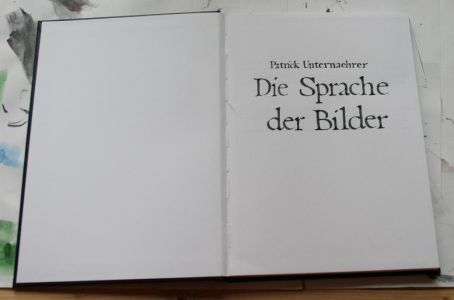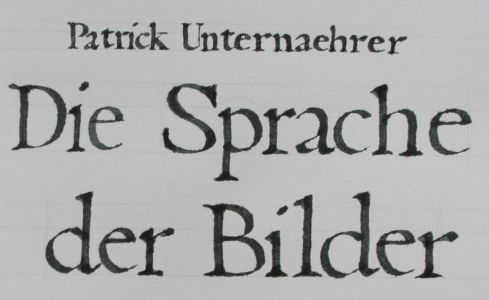
Franz. Renaissance Antiqua mit Breitband Feder schreiben?
Ich habe ein Frage bezgl. der Handhaltung beim Schreiben mit einer Breitbandfeder. Unser Lehrer hat uns immer gesagt (als wir mit dem Pinsel typische geometrische Formen zeichneten) wir sollen mit der Hand nicht den Winkel verändern um gewisse Formen einfacher zeichnen zu können.
Nun versuche ich selbst mit einer Breitbandfeder, von ca. 4-5 Dicke, in dieser Franz. Ren. Antiqua zu schreiben. Aber bei ein paar Abstrichen muss ich einfach sagen 'Wie zum Teufel soll das gehen!?'.
Hier ein Beispiel meiner Probleme (dieser Schriftschnitt ist jedoch für den PC Gebrauch, aber viel ist ja nicht anderst zur Originalen):
Diese Fraktur Schrift ist übrigens auch solch ein Handverränker.
Mein Anliegen ist eigentlich sehr geringfügig mir geht es nur darum wie es der Professionelle Kalligraph macht. Wenn es ok ist seine Hand in andere Winkel zu drehen um solche Abstriche zu erzielen wäre es kein Problem. Mich verwirren halt nur die Worte meines Lehrers (und bei den Eigenschaften steht auch 'schräge achse', also kann man doch nicht einfach die Achse drehen!?)
Die französischen Renaissance-Antiquas waren ja bereits Druckschriften und hatten sich als solche schon ein Stück von der Handschrift entfremdet (ich könnte auch positiv formulieren: emanzipiert). Der Duktus stimmt natürlich noch, aber manches ist so ohne weiteres nicht mehr mit händischen verfahren einfach nachzubilden.
Wäre es Dir möglich, einmal eine solche Arbeit hier zu zeigen?
Nicht zur Kritik zu stellen, nur zu zeigen.
Mich interessiert das.
Mir selbst war das Schriftenzeichnen in meiner Ausbildung immer ein Graus. Ich kann das nicht.
Unser Lehrer hat uns immer gesagt (als wir mit dem Pinsel typische geometrische Formen zeichneten) wir sollen mit der Hand nicht den Winkel verändern um gewisse Formen einfacher zeichnen zu können.
Dein Lehrer hat ja explizit "gewisse Formen" gesagt, was richtig ist. Ansonsten gilt wie überall: Keine Regel ohne Ausnahme. Und als Randbemerkung sei mir die Bemerkung erlaubt, dass das Schriftschreiben wohl die allerbeste Methode ist, das Wesen der Buchstaben zu erfahren und vielleicht sogar zu begreifen.
Dennoch empfind ich es als ein wenig dillettantisch wie ein blöder x Mal den Arm verstellen, aber wie gesagt sind dies ja Druckschriften die bereits ein wenig von der Handschrift 'emanzipiert' ( :lol: ) sind.
@ Georg: Ja, klar! Ich habe ein paar Beispiele hier geuppt
Hier habe ich mich in einer Kapitalis Quadrata versucht:
Diese Schrift habe ich gewählt weil Fibonacci um das 1-2 Jahrhundert lebte. Es wird eine Zeichnung wo ich Studien über Tannzapfen mit Fibonacci-Reihen mache.
Hier haben wir in der Schule eine Anglaise nachgezeichnet (auf einem Raster, deswegen das Transparentpapier - durchgepaust habe ich jedoch nicht wie viele andere in meiner Klasse! 8) )
Hier mussten wir unser Geburtsdatum in einer Schmall Grotesk zeichnen, mit Reisschiene und Technograph Bleistift
Hier habe ich mich in der Fraktur probiert. Noch nicht so schön ich weiss
PS: Wortzwischenräume finde ich bei manueller Kalligraphenarbeit extrem schwierig, beinahe unmöglich zum berechnen, deswegen mache ich das meistens aus dem Bauchgefühl
(Fibonaccis Geburtsdatum wird allerdings auf ca. 1170 datiert. Man hat keine Aufzeichnungen über das tatsächliche Geburtsdatum gefunden.)
Die In der Kalligrafie gibt es keine Möglichkeit, Wortzwischenräume zu berechnen. Das Bauchgefühl reicht allenmal aus, da man der Arbeit das Handwerk auch ansehen darf. Ich dachte, ihr würdet nur noch Klebfolie mit dem Plotter schneiden und aufkleben. Wo gehst Du zur Schule?
ermm.... 1000 Jahre - mein ich doch :D
Aber eine Rotunda würde passen? Die wurde ja in Italien entwickelt und dort hauptsächlich benutzt. In Geschichte bin ich noch nicht so überlegen.
Die Rotunda wurde vom 13. bis ins 15. jahrhundert geschrieben, also eher später. Die karolingische Minuskel vom 8. bis ins 12. Jahrhundert müsste passen - die ist auch einiges einfacher hinzukriegen und lässt sich ziemlich flüssig schreiben.